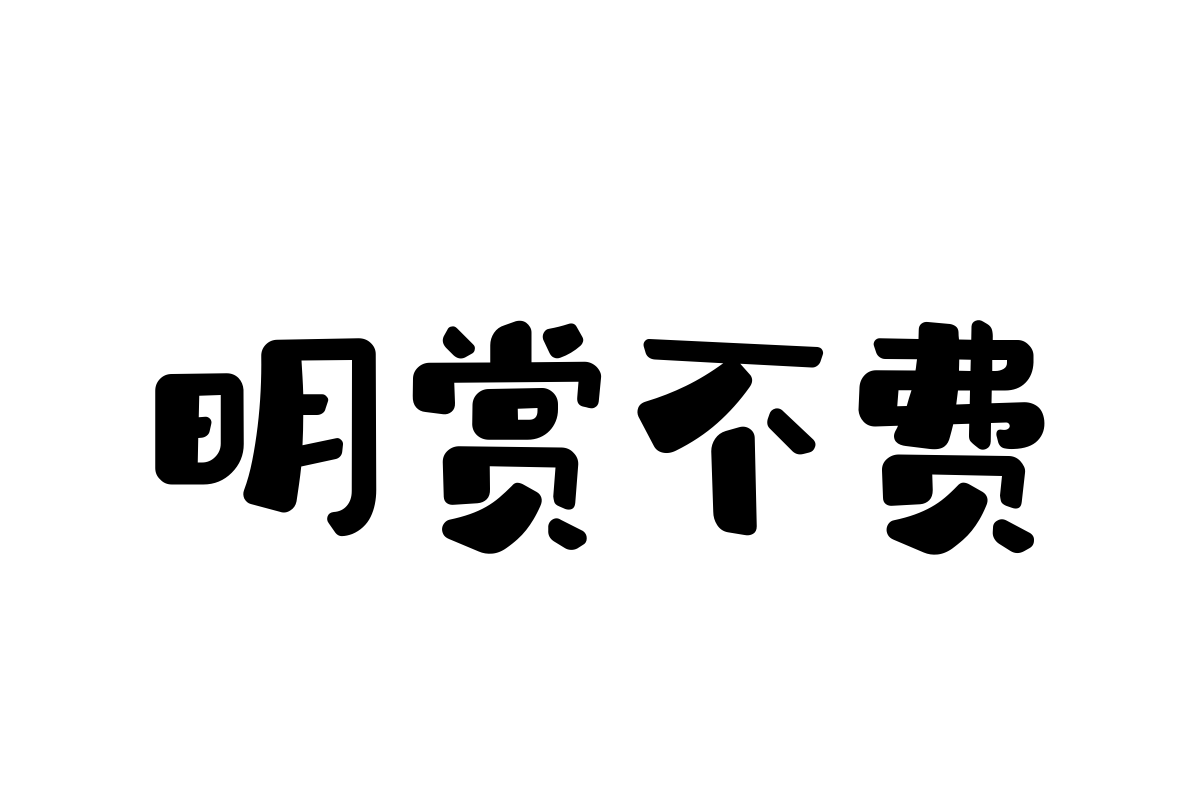
汉仪铸字树袋熊是一款具有独特风格的字体,它以树袋熊的形象为基础,创造出了独特的字体风格。这款字体笔画流畅,结构紧凑,给人一种自然、轻松的感觉。它的线条粗细适中,既有力量感又不失柔和,非常适合用于设计海报、广告、包装等需要突出视觉效果的场合。同时,这款字体也适合用于儿童插画、儿童书籍封面等需要温馨、可爱的设计。